사적으로 아름다운-2 : <자연사>
연재 ‘사적으로 아름다운’을 통해 세상에 존재하는 여러 책 중에 조금 더 필자 개인에게 아름답게 다가오는 책에 대해 자세하게 이야기한다.
사적으로 아름다운 – 2 : <자연사>
자끄 드뉘망 지음, 울리포프레스, 2015
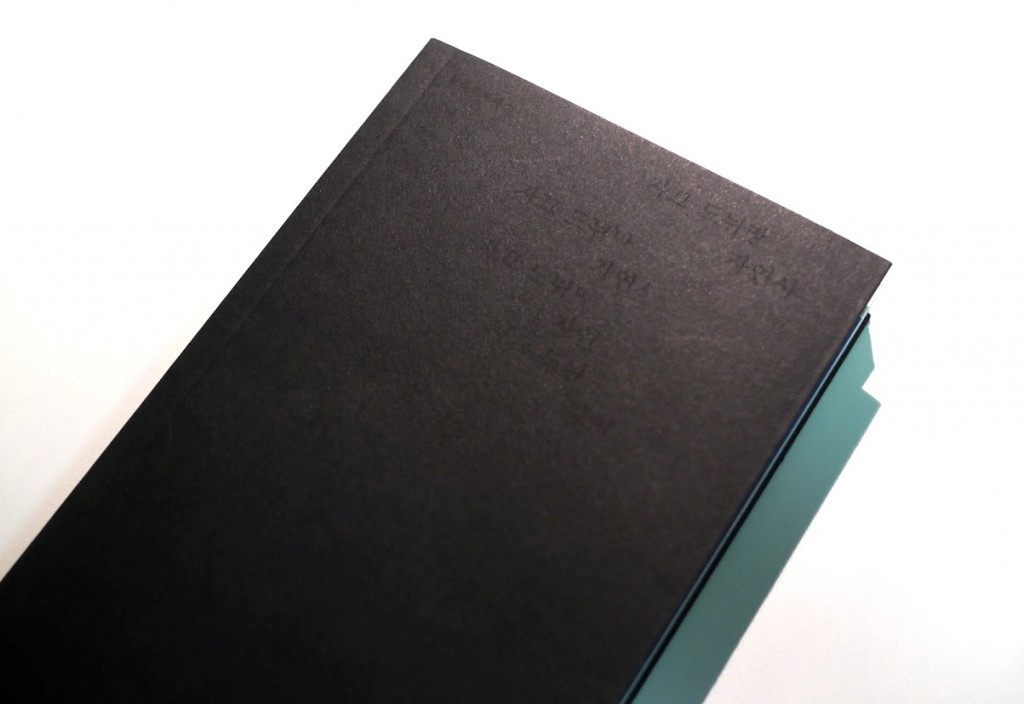
1편에서 이야기한 <시청각문서 1-[80]>의 표지가 백색 바탕 위에 문자만으로 세운 구조물이라면, <자연사>의 표지는 먹색 바탕 위에 문자가 물러날 수 있는 끝까지 가보려 한다. 검정 종이 위 출판사명(울리포프레스), 제목(자연사), 저자명(자끄 드뉘망)이 먹1도로 인쇄되어 있다. ‘검정’이라는 단어를 기준으로 할 때 검정 바탕 위 검은 글자는 보이지 않아야 한다. 읽히지 않아야 한다. 하지만 종이의 검정을 만들어낸 잉크의 농도와 글자의 검정을 만들어낸 그것이 달라 <자연사>의 표지 텍스트는 ‘문자의 흔적’처럼 표기된다.
유년기 학교에서 붓글씨 연습을 위해 벼루에 먹을 갈던 때를 떠올려 본다. 검은 돌 위에 물을 담고 또 작고 검은 먹을 갈아 글을 쓰기 위한 색을 만들 때, 그 광경은 아직 활자로 활성화되지 않은 비석의 상태였다. 검은색을 붓에 묻혀 흰 종이에 쓸 때 비로소 인식 가능한 형태를 갖추는데 <자연사>의 표지는 이 쉬운 형태를 따르지 않고 어렵고 어둡게 최소화된 양각으로 형태를 숨긴다.
표지를 읽기 위해 독자는 책을 쥐고 이리저리 각도를 달리해 보게 되는데, 생각해보면, 어떤 집중과 행동이 필요하게끔 최대한 뒤로 물러나는 표지가 얼마나 되던가. 더 덜 읽히려는 표지. 글씨는 하단으로 내려갈수록 점차 해체, 무너진다. 이 표지 디자인은 검정 위 검정 글자로 모자라, 그렇게 쓰인 텍스트마저 허무는 방향으로 물러난다. 하단부에 결국 자음만 남은 ‘자연사’의 ‘ᄌ’과 ‘자끄 드뉘망’의 ‘ᄌ’은 영(0) 직전의 모습만 보여준다. 온라인서점 썸네일 크기에서도 인식 가능하도록 확대와 효과를 거듭하는 서체와 표지 디자인이 2016년 출판의 어떤 극단에 있다면, <자연사>의 표지는 그 반대 지점에 ‘불분명해서 유일한‘ 태도로 존재한다.
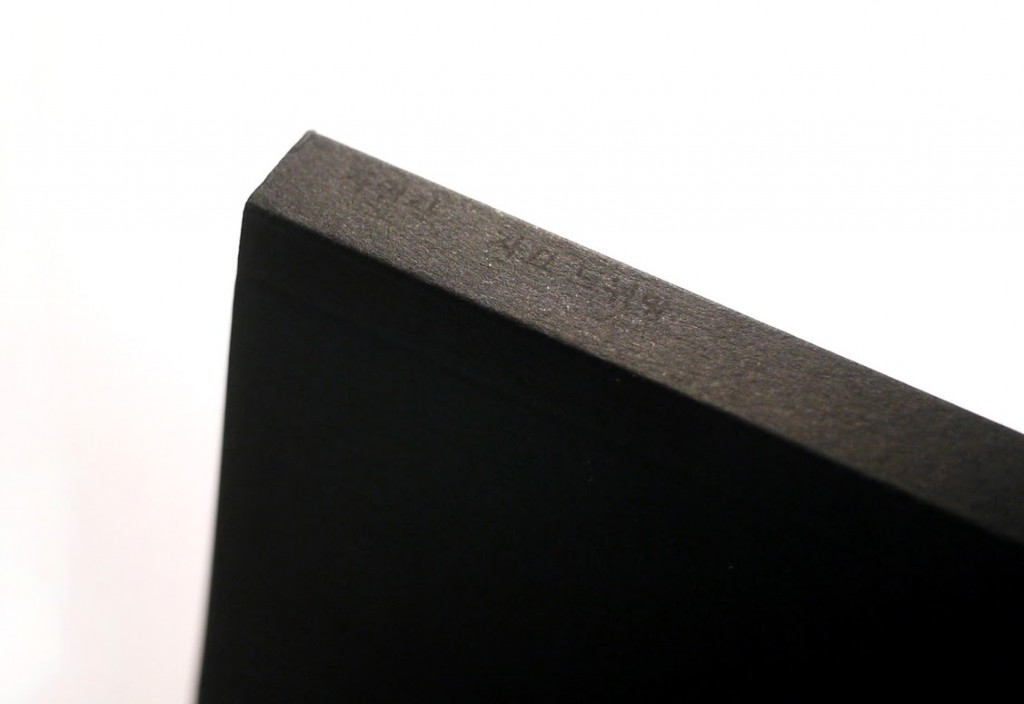
표2의 작가 소개문과 표3의 출판사 소개문도 마찬가지다. 백색 종이 위에 투명/백색을 실크스크린으로 넣든, 먹색 종이 위에 먹색 인쇄를 하든, 금색 종이 위에 금박을 앉히든, 어떤 방식이든 하나의 기술일 뿐이다. 디자이너의 능력은 ‘어떤 기술을 어떤 맥락으로 어떤 곳에 사용할 것인가’ 민첩하게 판단하는 감각에 있다고 생각한다. 대단한 기술을 목록화하고 이를 어떤 내용이 따라오든 무관하게 입력, 적용한다면 시각적으로 ‘압도적이기만 한’ 작업이 탄생할 것이다.
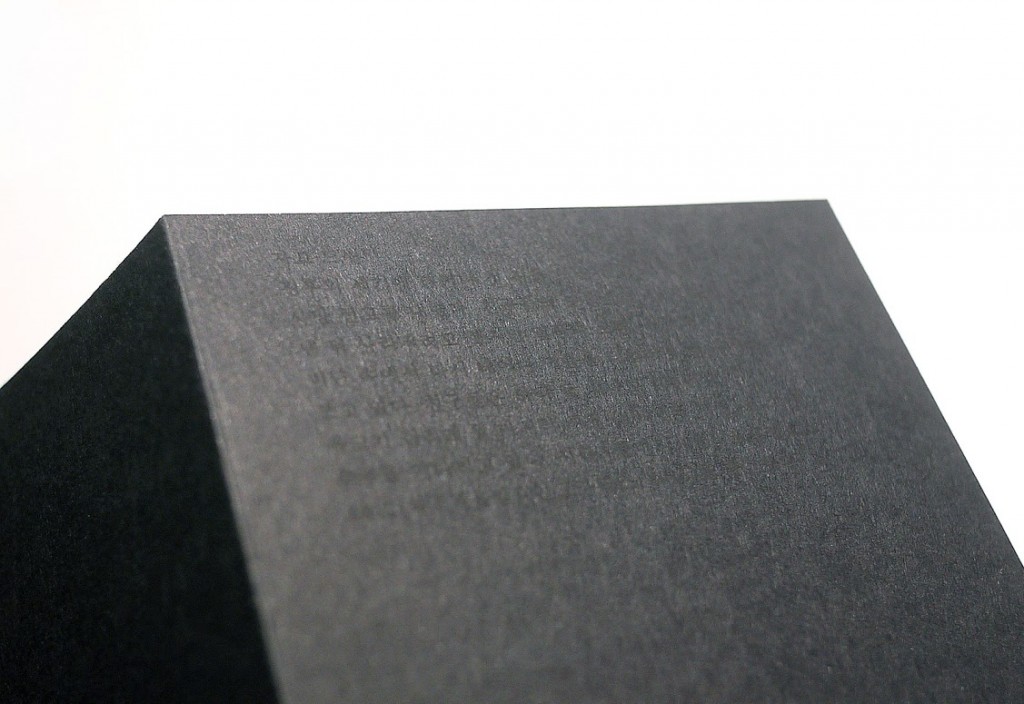
전용완 디자이너는 무용한 책을 만드는 출판사에서 발행한, ‘첫 시를 쓰는 순간 스스로 사망 선고’를 내린 시인이 쓴 <자연사>라는 시집, 3중의 죽음으로 중첩된 시집을 아름다운 어둠 속으로 밀어 넣는다. 이 책은 디자이너로 인해 4중의 죽음을 획득한다. 그리고 나는 독자에 의해 자주 읽히고 긁혀 끝내 표지의 글씨들이 완전히 사라져 앞표지와 뒤표지의 구분이 불가능해지는 순간을 생각한다. 그때 이 표지는 비로소 완전해질 것이다.